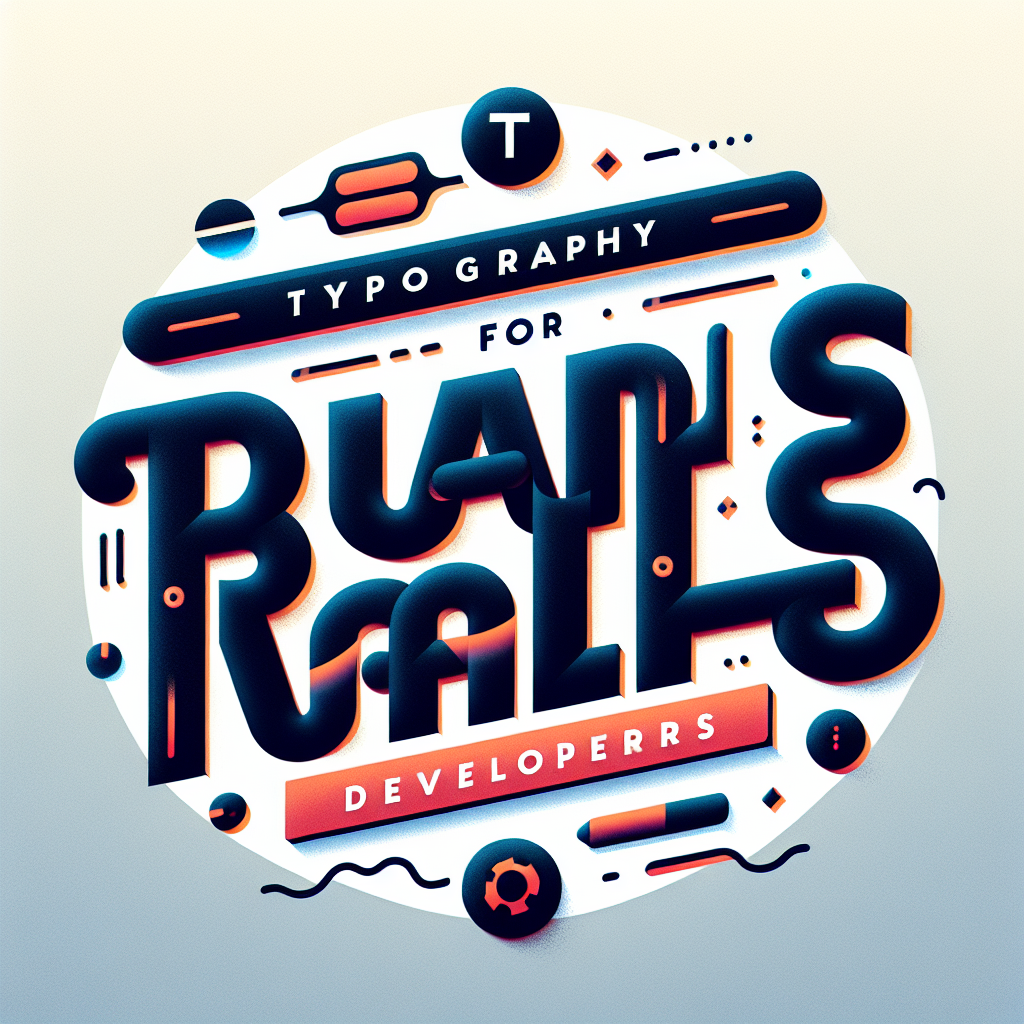
Usar tipografía profesional en una aplicación Rails marca la diferencia entre algo que parece correcto y algo realmente profesional. Primero, conviene distinguir tipos y fuentes: un tipo de letra o typeface es el diseño general como Inter o Helvetica, mientras que una fuente es una implementación concreta con peso y tamaño. Los desarrolladores web modernos deben priorizar el formato WOFF2 por su compresión y compatibilidad; evitar TTF u OTF para la web y no usar WOFF antiguo.
En Rails lo más práctico es autoalojar las fuentes en app/assets/fonts para controlar la carga y evitar dependencias externas. Si es posible, usar fuentes variables reduce el número de archivos y el tamaño total, permite transiciones suaves entre pesos y mejora el rendimiento. Si no hay variable fonts, usar varios archivos WOFF2 con mapeo de pesos apropiado y font-display swap para evitar texto invisible durante la carga.
Las funciones avanzadas de OpenType como ligaduras, kerning y números tabulares pueden activarse desde CSS para pulir la apariencia de la interfaz. Para rendimiento y coherencia en interfaces, considerar las fuentes del sistema con font-family usando keywords como system-ui y ui-sans-serif, que aprovechan las tipografías nativas en macOS, Windows, Android y Linux.
Al elegir un tipo profesional busque mayor x-height para legibilidad en tamaños pequeños, familias sans-serif para interfaces y varias intensidades de peso para crear jerarquía sin cambiar de familia. Mantenga la combinación de tipos simple: una familia principal para la UI y, si hace falta contraste para un blog o contenido largo, una familia serif para el cuerpo de texto.
Si usa Tailwind CSS, puede mapear fuentes con variables CSS para integrar su tipografía en las clases font-sans, font-serif y font-mono y mantener un control centralizado. Herramientas adicionales como size-adjust, ascent-override y descent-override ayudan a minimizar cambios de diseño cuando las fuentes se cargan o cambian.